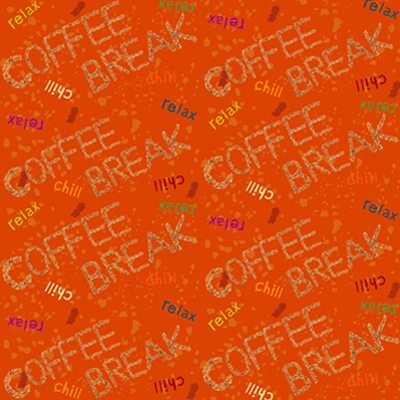
COFFEE BREAK
チャフ(もみ殻)をふんだんに使った香り高いパターンです。
コーヒーのもみ殻を一文字一文字紙に貼り付けて作るのがとても大変でした。原画のニュアンスが出て良いと思います。(澤田和弘)
コーヒーのもみ殻(chaff)を利用して作ったチャフフォントと、その原画を使用して作ったパターンです。背景には、カンマ(小休止)と、チャフのシルエットを散りばめています。「渋谷でコーヒーブレイク」が、今回のチームコンセプトでもあるので、そちらに相応しいパターンにしました。(須田千秋)